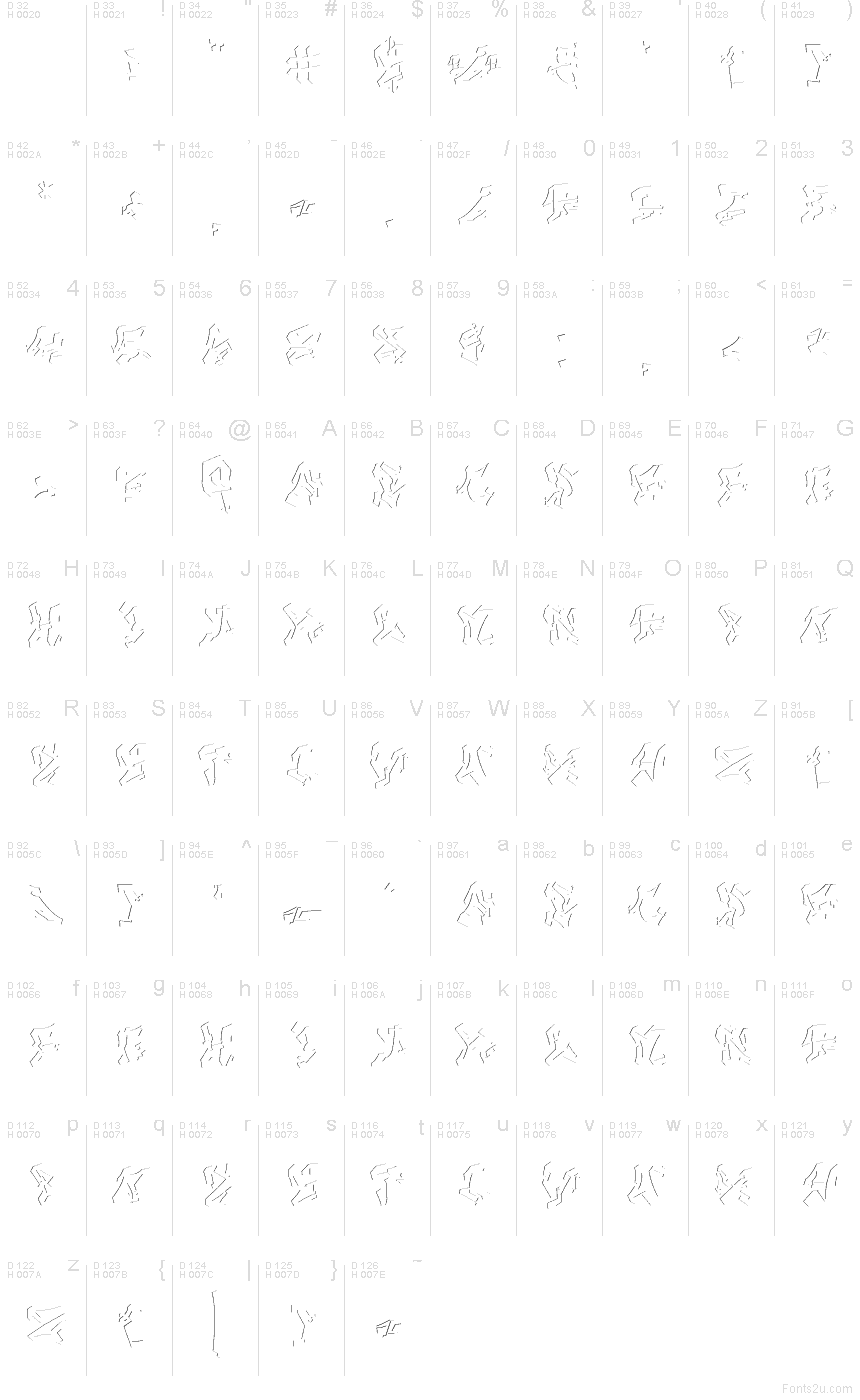
Il carattere Nightclaw Vandal Inner Solid di Muhammad Panji Ramdhani e Ferbiya Rahmat di Cikareotype fa parte della famiglia Nightclaw Vandal Inner ed è un font graffiti gratuito. I tratti sembrano graffiati da una lama e scheggiati, con linee interne che ricordano la vernice scrostata su un muro di cemento. Il ritmo angolare lo rende rumoroso e irrequieto, anche quando viene impostato con una spaziatura stretta.
Con Nightclaw Vandal Inner Solid creerai titoli d'impatto per loghi streetwear, poster di skate, copertine di album, miniature di giochi, volantini di eventi, pacchetti di adesivi e intestazioni YouTube dal sapore grintoso. Questo font gratuito dà il meglio di sé nelle dimensioni grandi: lascia che la texture respiri. Abbinalo a un grottesco sans serif pulito per il testo di accompagnamento, così da mantenere il caos sotto controllo.